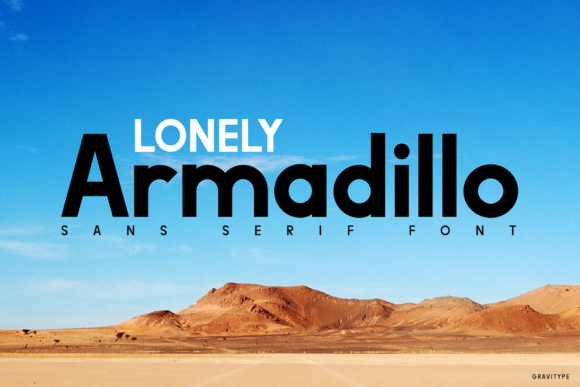
Creativefabrica Lonely Armadillo Font 2021
[Creativefabrica] Lonely Armadillo Font (2021)
Lonely Armadillo - это адаптируемый, современный и аккуратный шрифт sans serif.
Его можно легко подобрать к невероятно большому набору проектов, поэтому добавьте его в свои творческие идеи и обратите внимание на то, как он их выделяет!